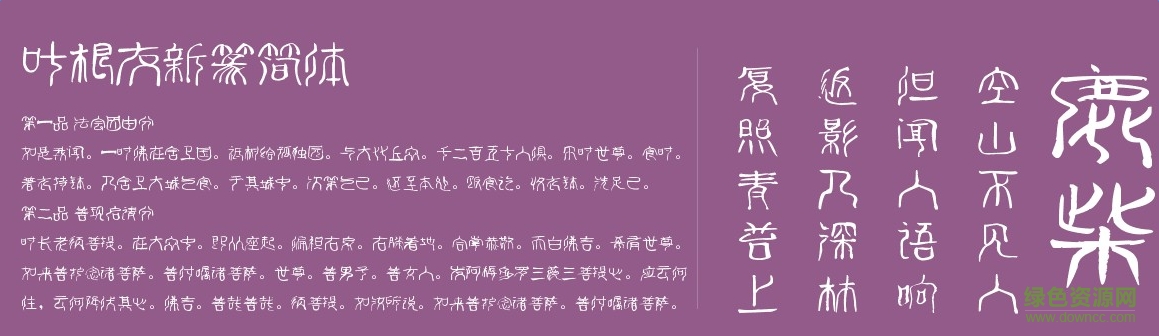
葉根友新篆簡體字體是由中國書法奇人,五筆同書世界首創(chuàng)者,連筆空心字吉尼斯世界紀(jì)錄保持者葉根友先生親自書寫的一款字體,是葉根友先生平時(shí)書寫最多的一種,也是最為實(shí)用的風(fēng)格。字體大方,流暢。歡迎下載!
葉根友新篆簡體是一款應(yīng)用于設(shè)計(jì)方面的中文簡體字體,字形曲線柔美,非常適合用于各類設(shè)計(jì)當(dāng)中,讓你的主題更鮮明,效果更為明顯。有需要的朋友趕快來綠色資源網(wǎng)下載使用吧!